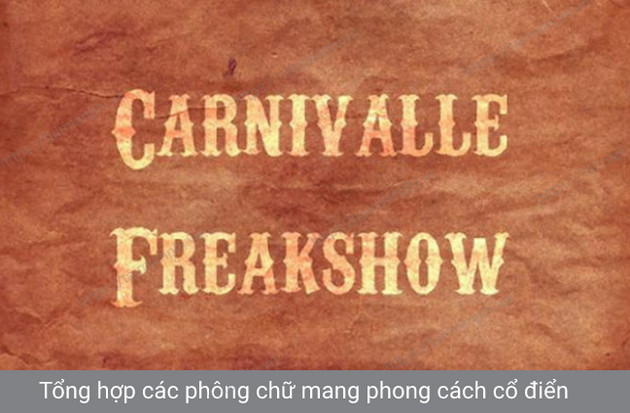
Font chữ cổ
Font chữ cổ phù hợp cho nhà thiết kế và những ai yêu thích nghệ thuật truyền thống. So với các phông chữ hiện đại, bộ font này mang đến một cảm giác tinh tế và hấp dẫn, giúp thiết kế của bạn nổi bật hơn.
Tính năng nổi bật
- Phong cách cổ điển: Mang đến sự thú vị cho các thiết kế mang đậm ảnh hưởng từ những thời kỳ khác nhau.
- Độ sắc nét cao: Đảm bảo mọi chữ cái đều rõ nét trong từng chi tiết nhỏ, giúp thiết kế luôn hoàn hảo.
- Thích hợp cho nhiều loại hình thiết kế: Từ thiệp mời, poster đến logo, font chữ cổ có thể áp dụng linh hoạt.